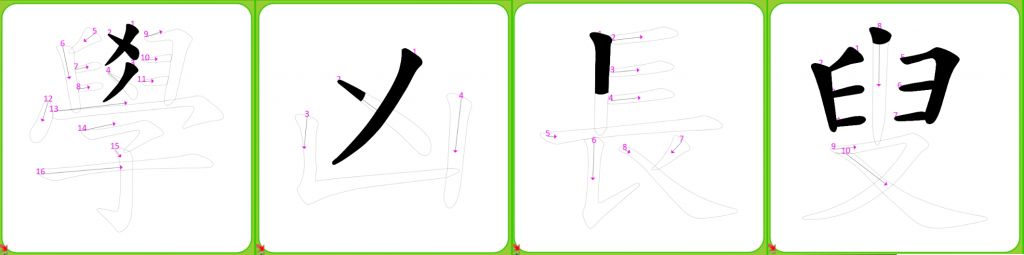
41. 教導學童學習生字時,指導正確的筆順,可以掌握字體的間架結構,達到 寫出正確、美觀字體的目標。下列選項字體的筆順說明,何者正確?
(A) 學:先寫中間的爻,再寫左右兩個部件
(B)凶:先寫ㄩ,再寫ㄨ
(C) 長:第一筆先寫橫畫,第二筆寫豎畫
(D)叟:先寫中間豎畫,再寫左右 兩個部件
B)凶:先寫ㄩ,再寫ㄨ (先寫ㄨ)
(C) 長:第一筆先寫橫畫,第二筆寫豎畫 (先寫豎筆)
(D)叟:先寫中間豎畫,再寫左右 兩個部件 (先寫左部件)
(B)凶:先寫ㄩ,再寫ㄨ (前後對調)
(C) 長:第一筆先寫橫畫,第二筆寫豎畫 (前後對調)
(D)叟:先寫中間豎畫,再寫左右 兩個部件 (前後對調)